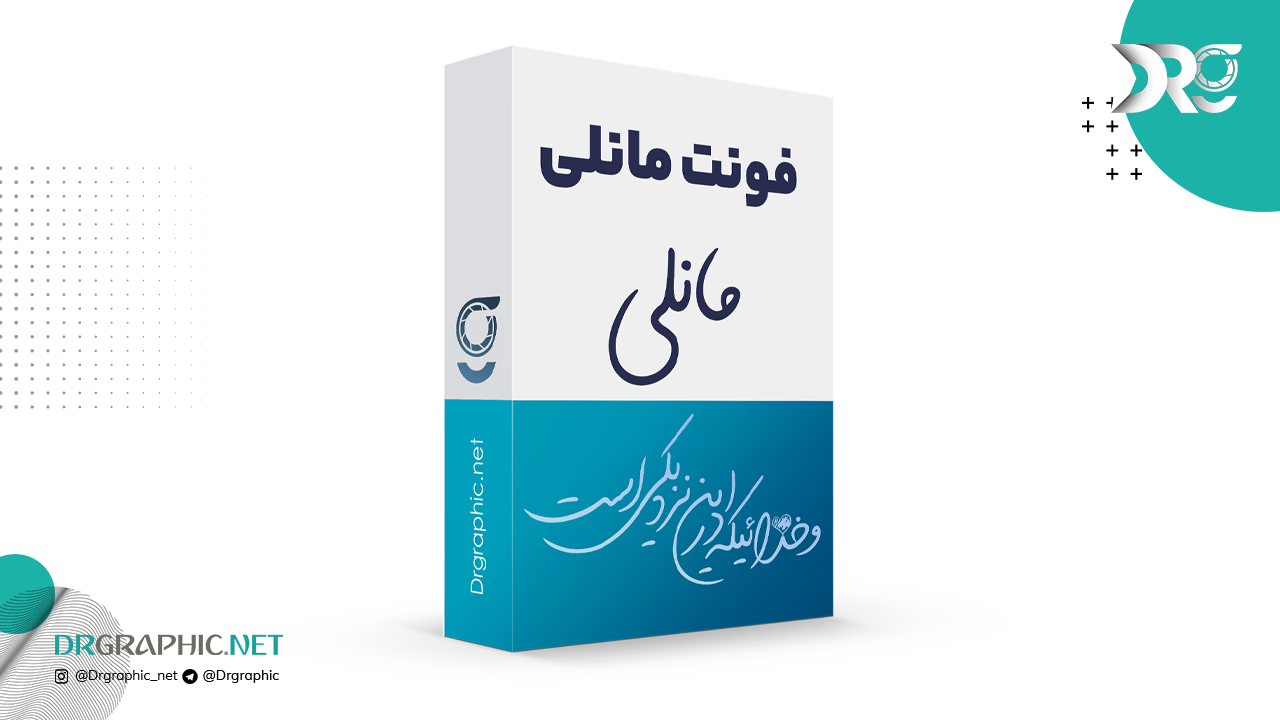
دانلود فونت مانلی
فونت مانلی به دست‌خط طبیعی خیلی شبیه است. در بسیاری از فونت‌های سبکِ دست نویس، حروف با دست طراحی شده سپس روی یک خط کرسی به هم متصل شوند، در حالی که فونت مانلی دارای کرسی سیال است.
علاوه بر کرسی سیال، فونت مانلی دارای ترکیبات بسیار زیاد، امکان ایجاد کشیدگی و حروف جایگزین متنوع است.
• مناسب برای استفاده به عنوان دست نویس
• مناسب برای تبلیغات
• مناسب برای پست اینستاگرام